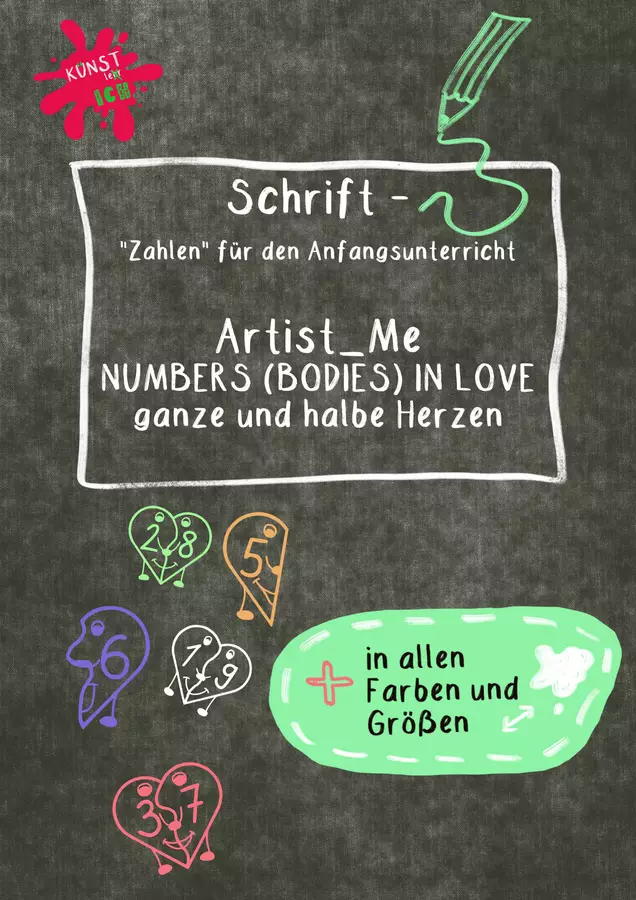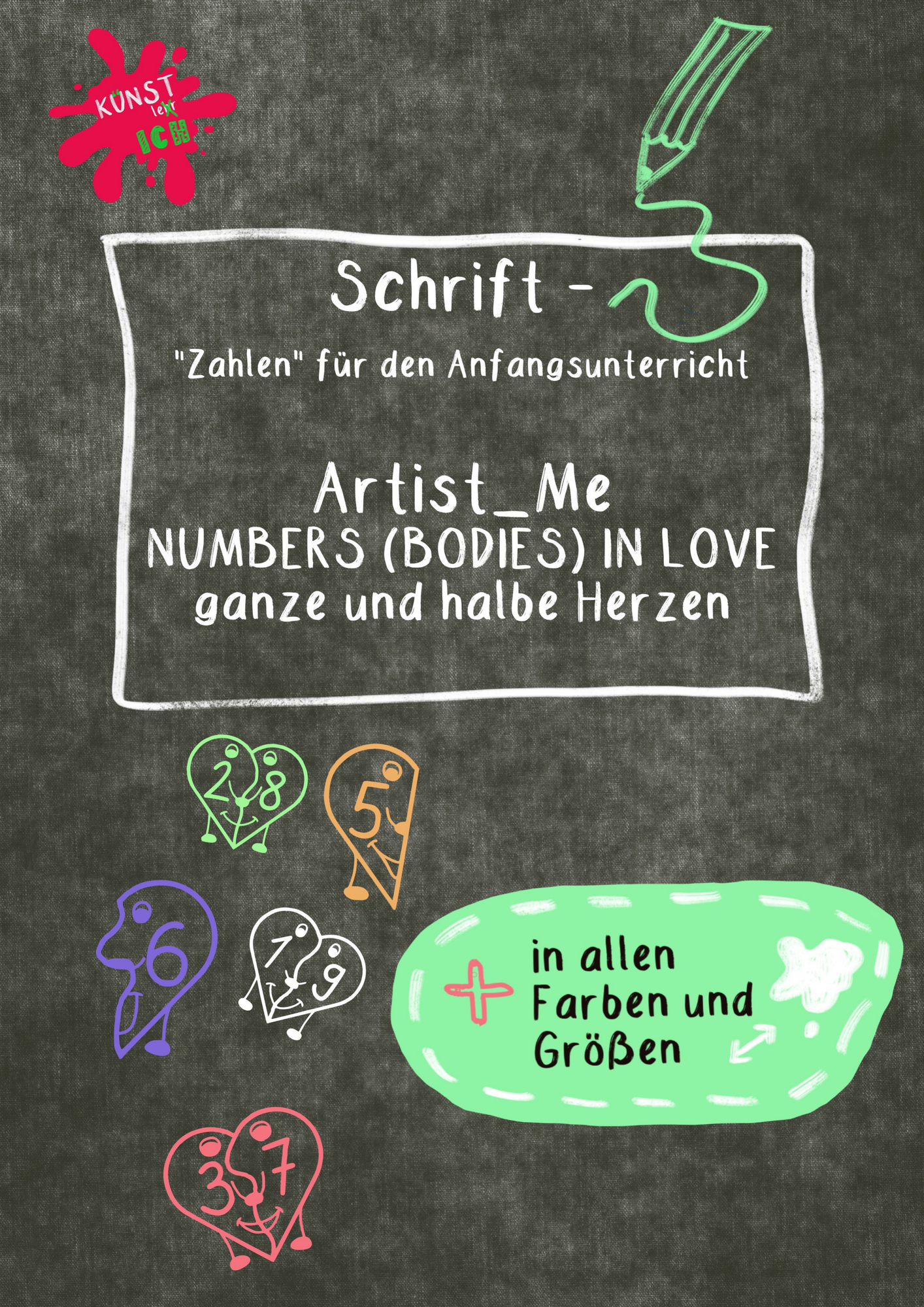
Poster - Schrift / Ziffern / Font - verliebte Zahlen - ❤ Artist_Me-Numbers In Love (Body) - ART.ist_ME // Kuenstler_Ich - Deckblatt
Mit dieser Schrift ist es ganz leicht individuelle Arbeitsblätter zu den verliebten Zahlen zu erstellen.
In dieser Variante liegen die Herzen mit Gesichtern und Körper vor! Sie sind daher nicht einfach von SchülerInnen auszuschneiden und zusammenzupuzzlen! Dazu eignen sich die beiden anderen Varianten!
Schrift / Ziffern / Font - verliebte Zahlen - ❤ Artist_Me-Numbers In Love (Body)